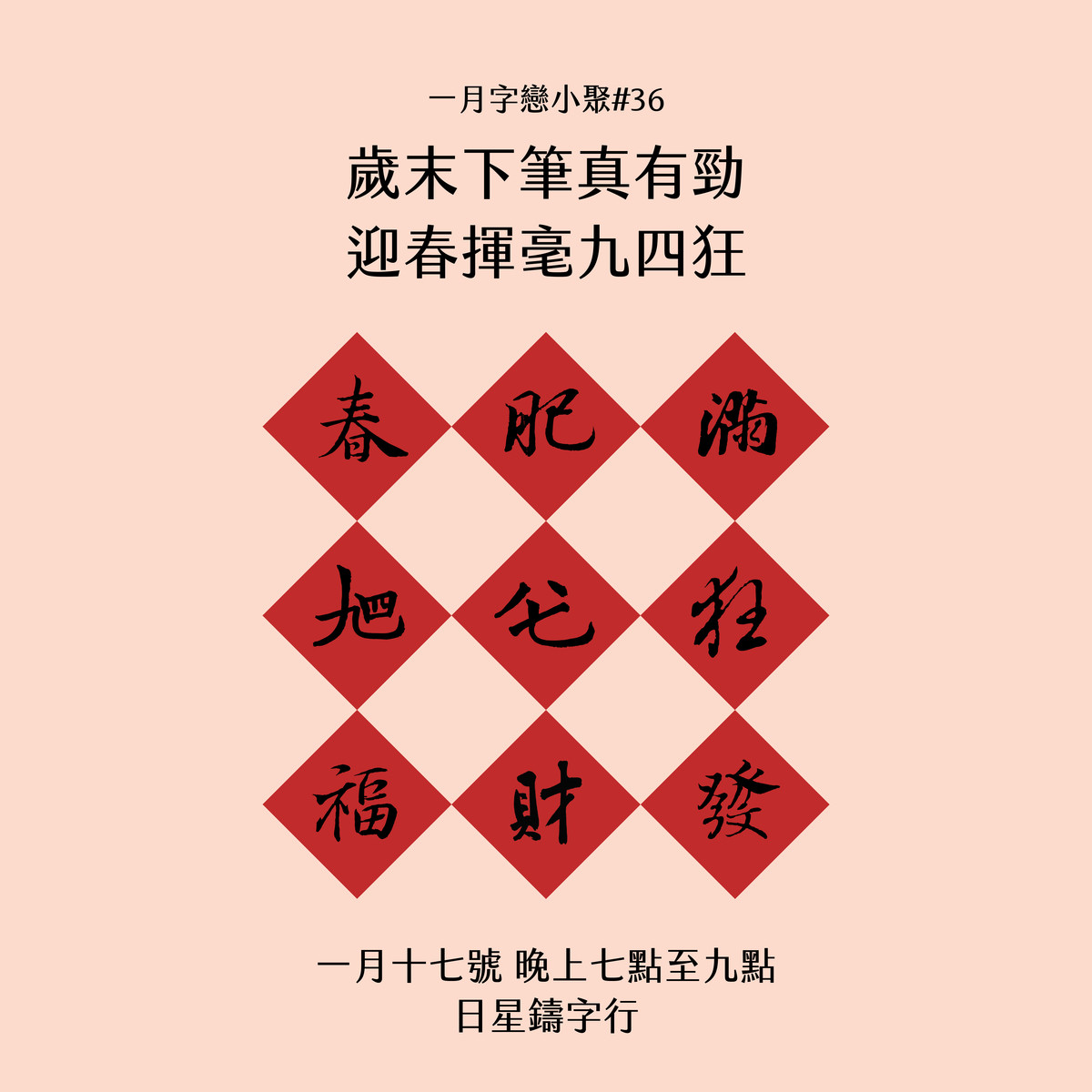
「這個純屬自嗨的活動到底為什麼可以又再辦一次?」
- 字戀週報
「因為最近有在練書法,寫完送大家回去貼沒問題的」
- 主辦者台北葉先生
「我寫了好多大字,後來都借跳樓大拍賣的老闆貼了」
- 參與者柯先生,2015
「過了一年之後,我果然還是不能靠賣春聯賺壓歲錢」
- 參與者蘇先生
「字帖可以讓大家參考,但不可以偷走」
- 日星張老闆
★★★★★
“參與者一致五星好評”
“全台灣最莫名其妙的書法活動”
關於特別來賓
「筆畫是風格,白色是美。」
「框框裡面是心境,框框外面是環境。」
「控制墨量是技法。至於它會不會暈開,是天意。」
BY 書畫家 李憶含教授
李憶含教授,台灣人,1959年出生,台灣當代彩墨畫家,國立臺灣師範大學美術理論與創作研究系博士。自大學畢業後,便積極投入現代彩墨的探索與研究,是位深耕且具豐富畫歷的藝術家。深入傳統,從其承襲、推展並發揚,以「古法今用」的繪畫理念融匯本土新思維,呈現具東方精神、現代表現的台灣彩墨新風貌。超現實的圖式與象徵主義的語彙,不僅深富文學內涵與哲學思想,也表現出作品相當程度的成熟風貌。
李憶含教授同時也是 justfont 整個團隊都去拜的書法老師。繁忙打著的各種事業副本之餘,justfont 的大家都很享受每週二晚上李老師的書法課。不只學習技法、觀念,很多時候也是在享受老師各種神來一筆的評論,還有時不時玄之又玄的「講道」,對於創意工作實在是很好的養分。這次特別請老師出馬,參與這次的春聯創作活動,希望也能讓來參加的朋友感受一下老師的功力與魅力。